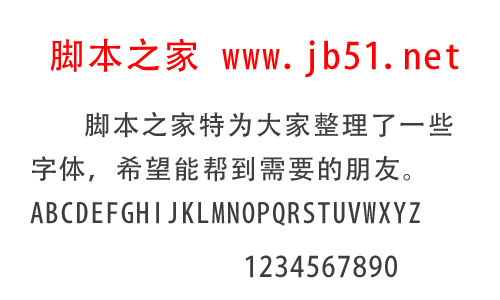
Adobe 黑體 Std R字體又稱之為adobeheitistd regular字體,是adobe官方專為設(shè)計(jì)師而開發(fā)的一款實(shí)用字體,該字體線條粗細(xì)適中,字形大方得體,整體效果非常出色,且字庫(kù)完整,能夠適用于產(chǎn)品包裝、廣告宣傳、出版印刷、商標(biāo)用字、商業(yè)網(wǎng)站、影視影像視頻、書籍出版印刷等設(shè)計(jì)領(lǐng)域,歡迎需要Adobe 黑體 Std R字體的朋友前來(lái)下載使用。